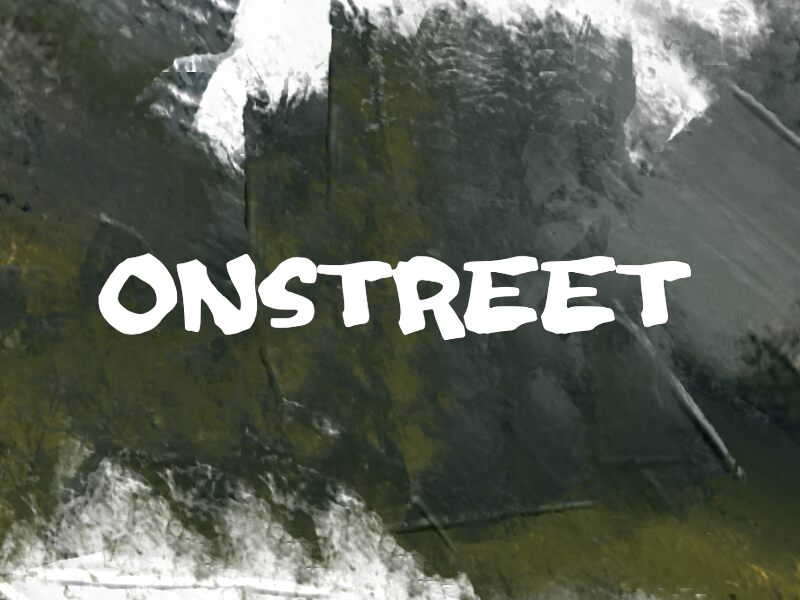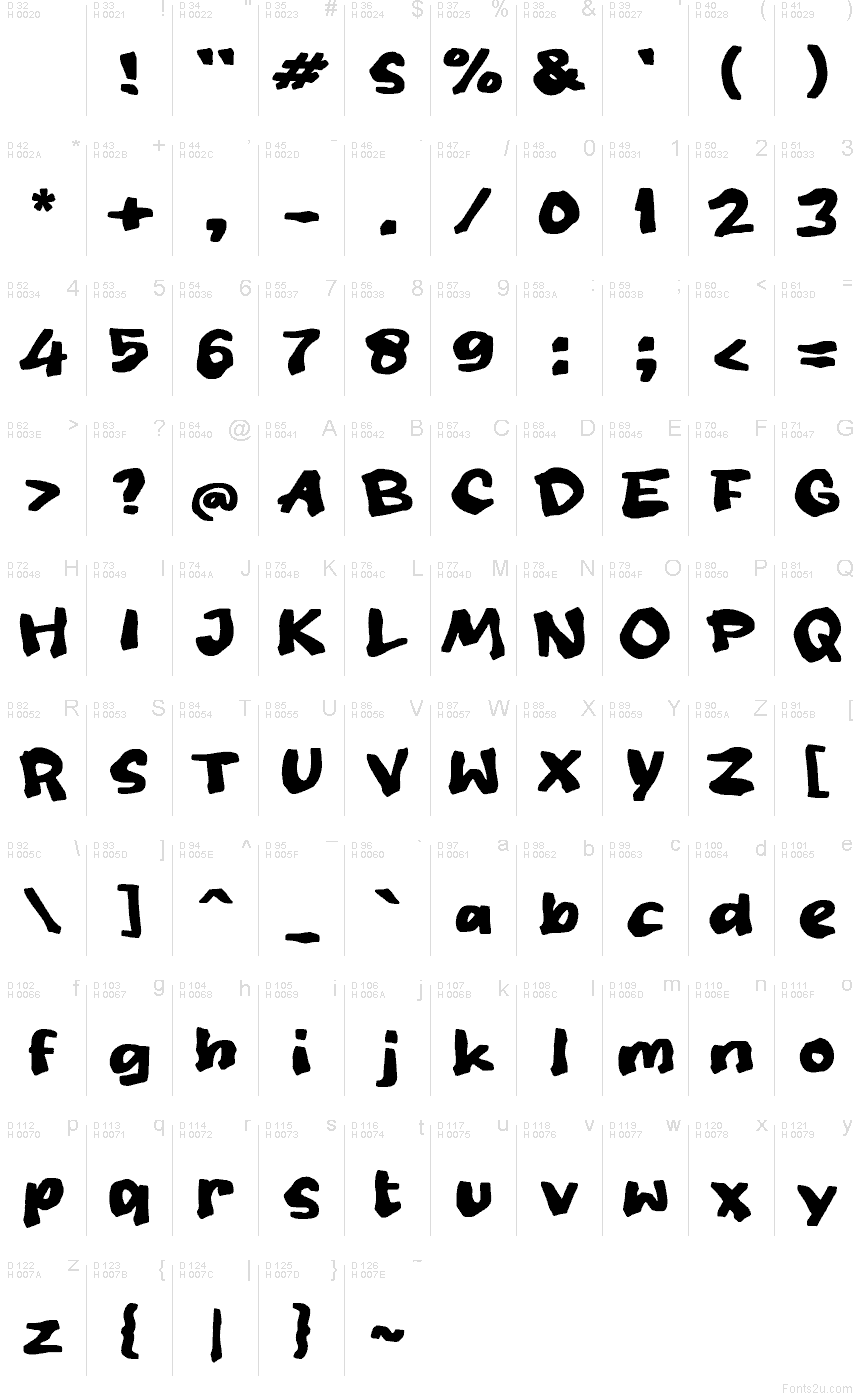
ONSTREET
ONSTREET od Wep je bezplatné graffiti písmo s plnými, ručne maľovanými tvarmi, ktoré pôsobia, akoby boli rýchlo nakreslené hrubým fixom. Nerovné okraje, stlačené spoje a asymetrická vyváženosť dodávajú písmenám surový rytmus pouličného tagu, čo je jasný kontrast k uhladeným komiksovým alebo „bublinovým“ štýlom.
Táto surovosť robí z ONSTREET silnú voľbu pre skate plagáty, obaly mixtapeov, streetwearovú grafiku, nadpisy letákov a príspevky na sociálne siete, ktoré vyžadujú úderný mestský nádych. Najlepšie vynikne v krátkych titulkoch, kde nepravidelné obrysy a plné čierne vyfarbenie vytvárajú výrazný grafický prvok, ktorý pôsobí skôr ako ručne maľovaný nápis než ako bežné písmo.